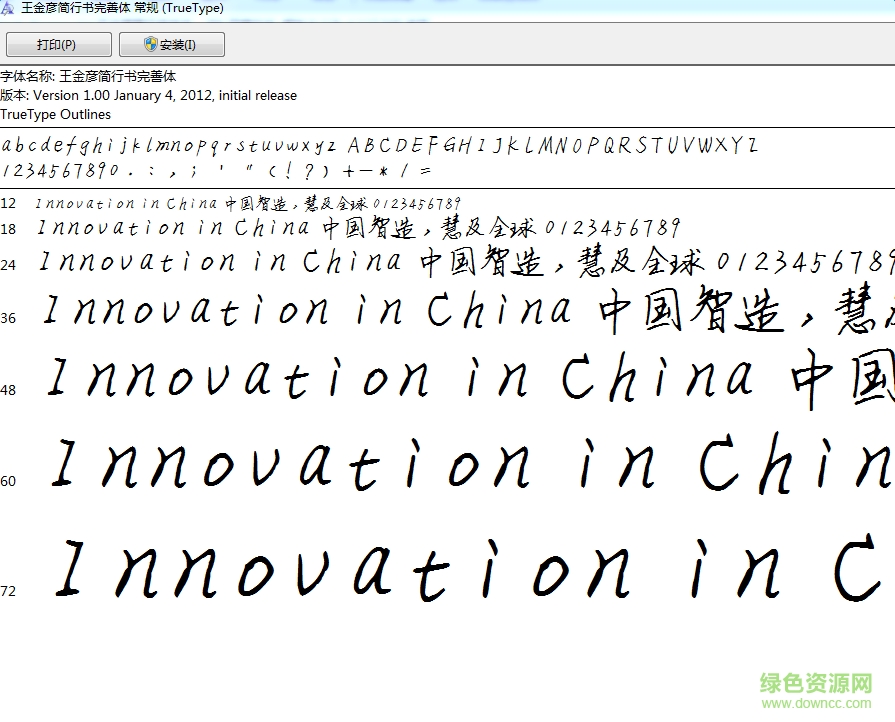
王金彥簡(jiǎn)行書完善體
王金彥簡(jiǎn)行書字體是一款經(jīng)典文雅風(fēng)格字體軟件,行書體筆畫隨意灑脫,卻別有一番韻味,介于草書與楷書之間,創(chuàng)意獨(dú)特,深受廣大書法家喜愛(ài),還有更多好看字體歡迎來(lái)綠色資源網(wǎng)下載體驗(yàn)!
王金彥簡(jiǎn)行書字體是一款應(yīng)用于藝術(shù)設(shè)計(jì)方面的簡(jiǎn)體中文字體,該字體筆畫細(xì)膩,尾部的甩尾有力且有豐富的筆觸細(xì)節(jié),大字效果突出且引人注目;并且最大程度還原作者書寫字形,細(xì)節(jié)表現(xiàn)完整,且字庫(kù)完整,可以廣泛應(yīng)用于名片設(shè)計(jì)、新聞媒體、宣傳海報(bào)、ppt、影視制作以及內(nèi)容用字等領(lǐng)域。
王金彥簡(jiǎn)行書字體